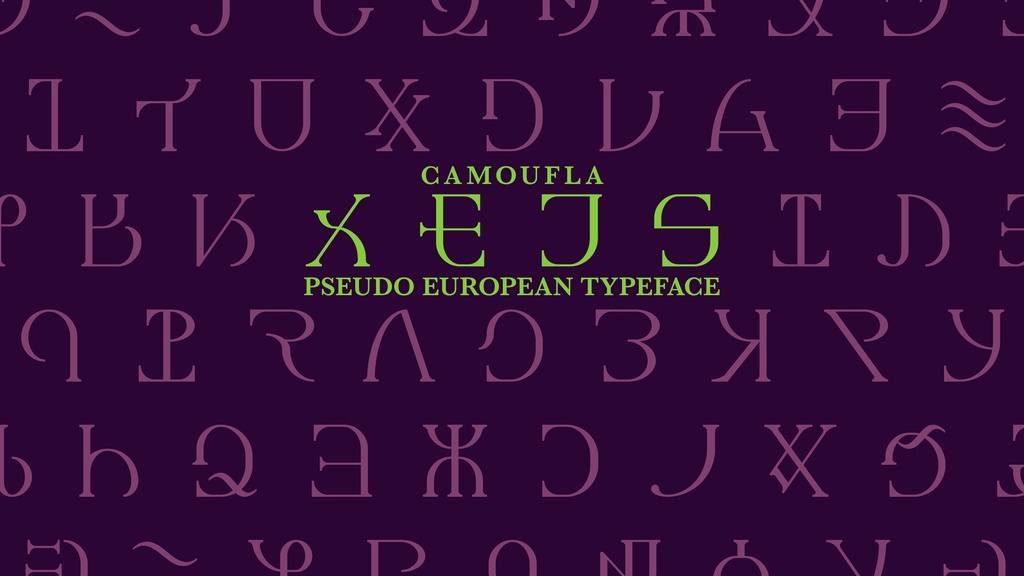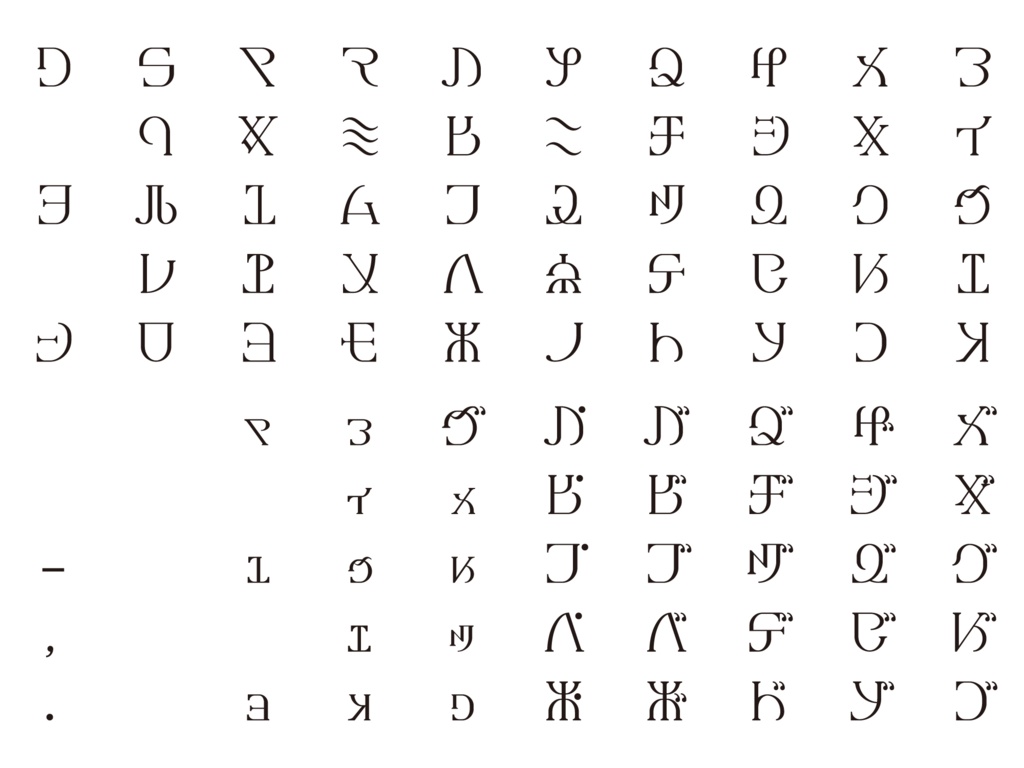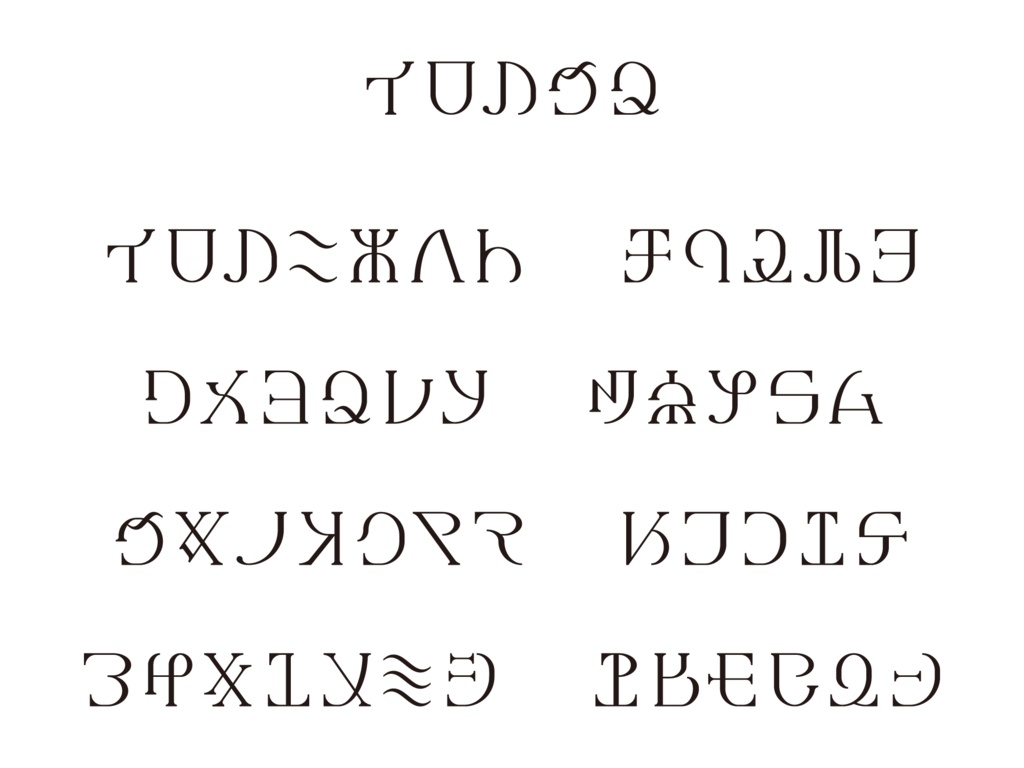
疑似欧文書体「カモフラ」/ Pseudo European Typeface “CAMOUFLA”
認知バイアスのトップダウン処理の性質を利用した、 欧文書体に見えるカタカナフォントです。 カタカナと「、」「。」「ー」を収録しています。 その他の文字や記号はなく、 游明朝体やヒラギノ明朝体などと合わせて使う想定で制作しています。 ※初心者の制作したフォントですので、至らない部分もあると思います。 利用規約 このフォントをダウンロードされた時点で、 利用規約に同意したものとみなします。 ・このフォントの著作権は製作者にあります。 ・フォントデータの改変や再配布を禁じます。 ・商用利用、非商用利用問わず使用可能ですが、 必ず著作権の帰属表示をお願いします。 ・このフォントの使用により生じたいかなる損害につきましても、 製作者は責任を負いません。